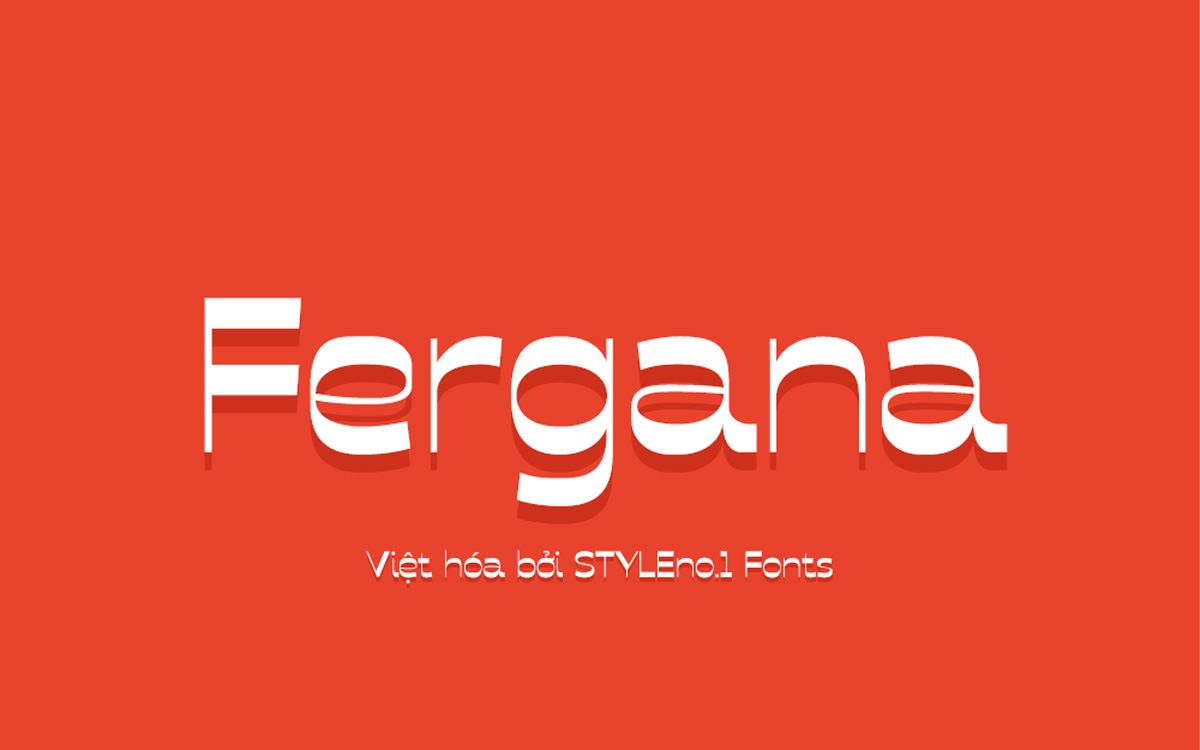
SVN-Fergana-Regular là font chữ vui vẻ, dễ thương mang phong cách hoạt hình, nổi bật với đường nét mềm mại, thân thiện và giàu cảm xúc. Kiểu chữ này đặc biệt phù hợp với các thiết kế dành cho trẻ em, đồ ăn, thức uống, sản phẩm cute, nội dung giải trí và những thương hiệu muốn xây dựng hình ảnh gần gũi, sinh động.
Không chỉ giúp nội dung trở nên bắt mắt hơn, SVN-Fergana-Regular còn tạo cảm giác tích cực ngay từ lần đầu người xem tiếp xúc. Font có thể được ứng dụng linh hoạt trong tiêu đề, bao bì, poster, banner, bài đăng mạng xã hội và nhiều ấn phẩm sáng tạo khác.
Font chữ vui vẻ, dễ thương, hoạt hình SVN-Fergana-Regular dành cho trẻ em, đồ ăn, food và thiết kế cute
Trong thiết kế hiện đại, font chữ không chỉ đảm nhiệm vai trò truyền tải thông tin mà còn góp phần thể hiện tính cách của sản phẩm và thương hiệu. SVN-Fergana-Regular là lựa chọn đáng cân nhắc khi bạn cần một font chữ hoạt hình dễ thương, có khả năng tạo không khí vui nhộn nhưng vẫn bảo đảm nội dung rõ ràng, dễ tiếp cận.
Với diện mạo mềm mại và trẻ trung, font chữ này có thể hỗ trợ hiệu quả cho nhiều lĩnh vực như giáo dục trẻ em, đồ chơi, truyện tranh, thực phẩm, bánh kẹo, đồ uống, nhà hàng, quán ăn, sản phẩm handmade hoặc các dự án truyền thông hướng đến giới trẻ. Thiết kế chữ giàu tính biểu cảm giúp thông điệp trở nên thân thiện hơn, đồng thời tạo điểm nhấn trực quan cho toàn bộ bố cục.
Phong cách hoạt hình vui vẻ, tạo cảm giác gần gũi
Điểm nổi bật của SVN-Fergana-Regular nằm ở phong cách hoạt hình vui tươi và dễ nhận diện. Các đường nét mang cảm giác mềm, thân thiện, giúp câu chữ bớt cứng nhắc so với những kiểu chữ hình học hoặc font văn bản thông thường. Khi được sử dụng trong tiêu đề, tên sản phẩm hay câu khẩu hiệu, font có thể nhanh chóng thu hút ánh nhìn và truyền tải tinh thần tích cực.
Đặc trưng này rất phù hợp với các thiết kế cần tạo cảm giác đáng yêu, hài hước hoặc giàu năng lượng. Bạn có thể sử dụng font cho những thông điệp ngắn như tên món ăn, chương trình khuyến mãi, lời chúc, tiêu đề truyện hoặc nội dung tương tác trên mạng xã hội. Khi kết hợp với màu sắc tươi sáng, hình minh họa ngộ nghĩnh và bố cục linh hoạt, SVN-Fergana-Regular sẽ góp phần tạo nên một tổng thể sinh động, dễ ghi nhớ.
Phù hợp với thiết kế dành cho trẻ em và giáo dục
SVN-Fergana-Regular là font chữ dễ thương phù hợp với nhiều sản phẩm dành cho trẻ em. Phong cách chữ vui vẻ giúp nội dung trở nên bớt trang trọng, tạo cảm giác thân thiện và khuyến khích trẻ chú ý đến thông điệp. Font có thể xuất hiện trên bìa sách, truyện tranh, flashcard, bảng chữ cái, tài liệu học tập, poster lớp học, thiệp sinh nhật hoặc bảng trang trí tại trường mầm non.
Khi triển khai thiết kế cho trẻ em, bạn nên ưu tiên cỡ chữ đủ lớn, khoảng cách chữ hợp lý và độ tương phản rõ ràng giữa chữ với nền. SVN-Fergana-Regular có thể được dùng làm font tiêu đề hoặc font tạo điểm nhấn, trong khi phần nội dung dài nên kết hợp với một kiểu chữ đơn giản để duy trì khả năng đọc. Cách phối hợp này vừa giữ được tinh thần hoạt hình đáng yêu, vừa giúp bố cục chuyên nghiệp và cân bằng hơn.
- Thiết kế bìa sách, truyện tranh và tài liệu học tập cho trẻ em.
- Trang trí lớp học, khu vui chơi, sự kiện hoặc tiệc sinh nhật.
- Thiết kế logo, tên thương hiệu đồ chơi và sản phẩm cho bé.
- Tạo tiêu đề cho video, nội dung giáo dục và bài đăng mạng xã hội.
Tạo điểm nhấn cho lĩnh vực đồ ăn, food và thức uống
Trong ngành ẩm thực, diện mạo vui nhộn của font chữ có thể kích thích cảm giác tò mò và giúp món ăn trở nên hấp dẫn hơn về mặt thị giác. SVN-Fergana-Regular thích hợp để trình bày tên món, nhãn sản phẩm, menu, bảng hiệu, bao bì bánh kẹo, ly nước, hộp đồ ăn hoặc nội dung quảng cáo cho quán ăn. Đặc biệt, font phù hợp với các thương hiệu hướng đến khách hàng trẻ, gia đình hoặc những người yêu thích phong cách cute.
Bạn có thể ứng dụng font cho cửa hàng bánh ngọt, trà sữa, kem, đồ ăn nhanh, đồ ăn vặt, thực phẩm handmade hoặc các sản phẩm theo mùa lễ hội. Những tiêu đề như “Món mới”, “Ngon mỗi ngày”, “Ưu đãi hôm nay” hay “Vị ngon đáng yêu” sẽ trở nên nổi bật hơn khi được trình bày bằng một kiểu chữ giàu cảm xúc. Font cũng có thể kết hợp với bảng màu vàng, cam, đỏ, xanh lá hoặc các tông pastel để tăng cảm giác ngon miệng và thân thiện.
- Thiết kế menu, bảng giá và bảng giới thiệu món ăn.
- Trang trí bao bì bánh, kẹo, đồ uống và thực phẩm đóng gói.
- Tạo banner quảng cáo, voucher và bài đăng khuyến mãi.
- Thiết kế tên món, slogan hoặc thông điệp trên cửa hàng trực tuyến.